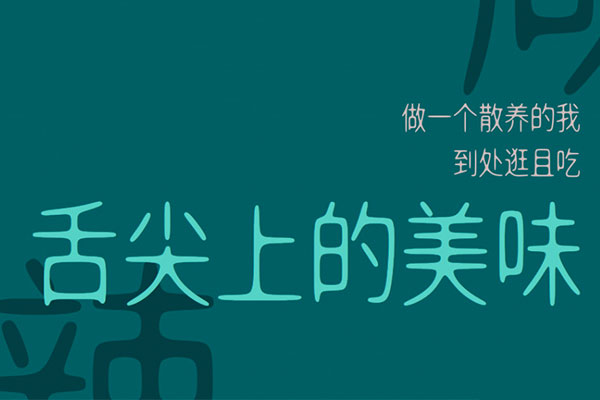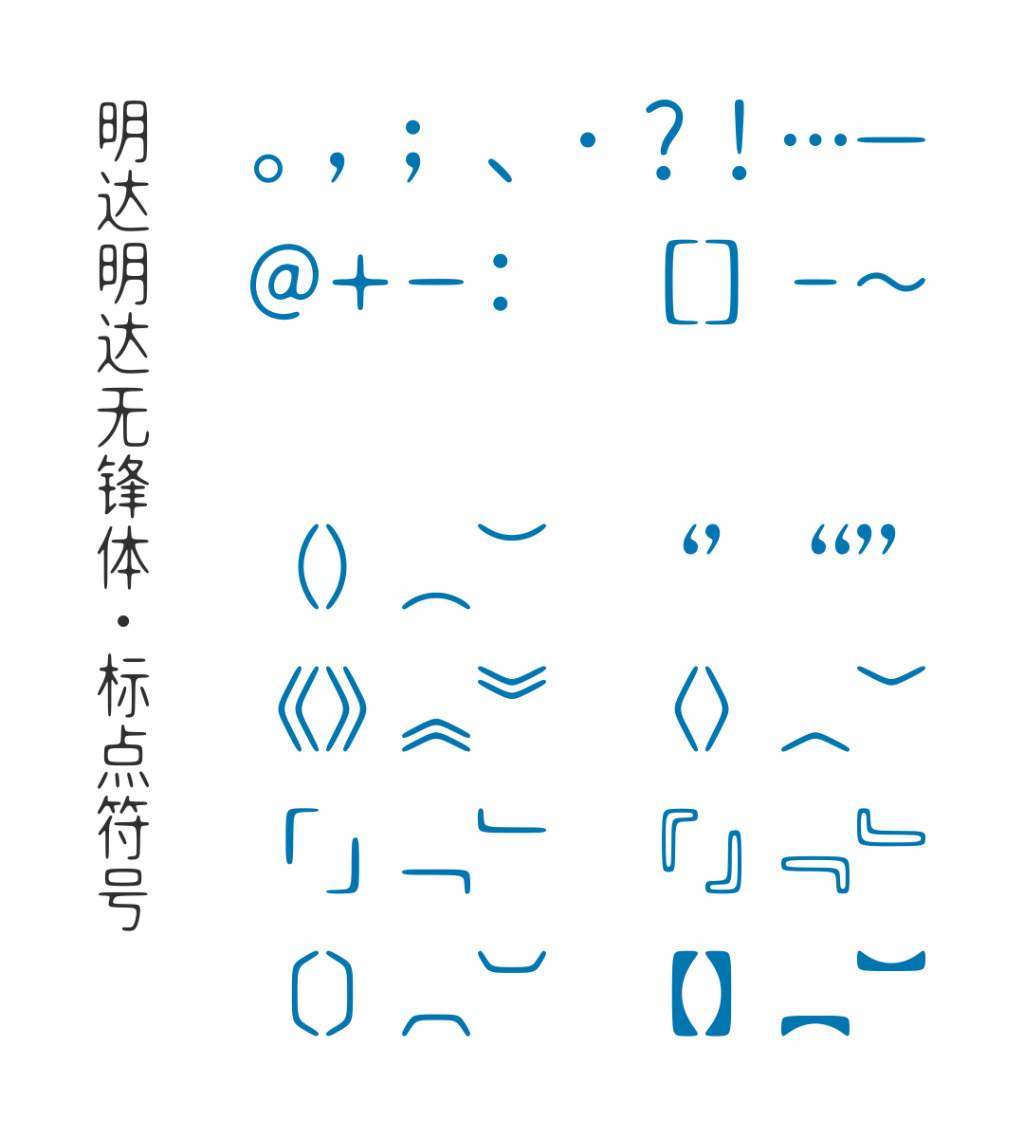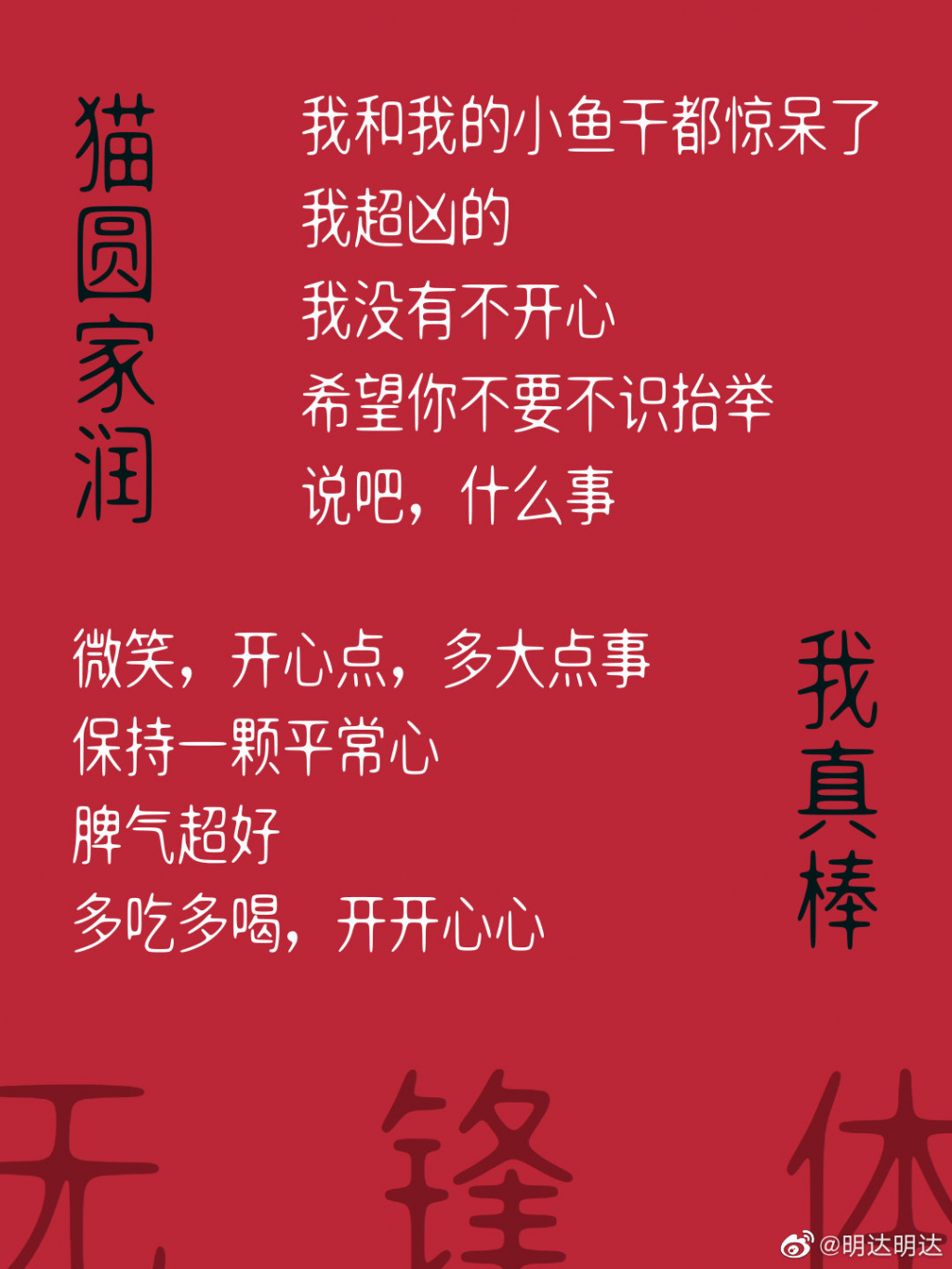
明达明达无锋体
明达明达无锋体是由微博网友“明达明达”发布的一款免费商用的字体。它包含了GB2312标准中的6763个汉字和49个全角中文标点符号,但不包含英文、数字。
该字体的特点是中宫放松,布局舒展,步进等宽。笔划略细,字身稍长,高宽比为5:4。在笔划布局上,它采用了中宫放松的黑体布局。这种布局在大体上参考了思源黑体(其布局非常均匀)和以前的竖型宣传字体,并根据具体的笔划形态冲突、重心变化和美观平衡进行了调整。整个字体看起来似水的凝聚,形成了“墨的无锋”,浑圆无折角,没有笔锋,因此被称为“无锋体”。
明达明达无锋体效果预览
明达明达无锋体字体效果预览